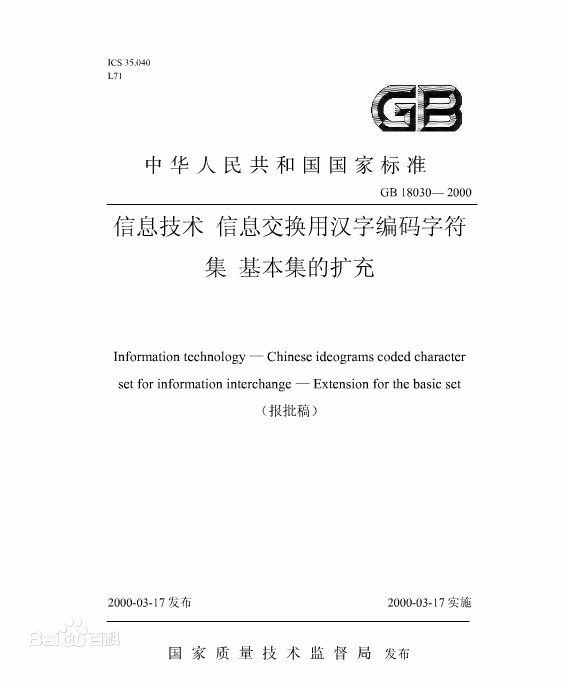
常见字体格式及编码资料
常见的字体格式有 TTF、EOT,一般使用 TTF。
TTF(TrueTypeFont)是Apple公司和Microsoft公司共同推出的字体文件格式,随着windows的流行,已经变成最常用的一种字体文件表示方式。
字库是输出设备的一个组成部分。由于汉字不同干西方字体,字符集非常庞大,不能用单字节表示,因此postscript level i的rip不能使用汉字,很多西文软件也不支持汉字。
桌面出版系统使用的字库有两种标准: postscript字库和truetype字库。这两种字体标准都是采用曲线方式描述字体轮廓,因此都可以输出很高质量的字形。
常用的字库标准是truetype字库,truetype字体是windows操作系统使用的唯一字体标准,macintosh计算机也用 truetype字体作为系统字体。
truetype字体的最大优点是可以很方便地把字体轮廓转换成曲线,可以对曲线进行填充,制成各种颜色和效果,它可以进一步变形,制作特殊效果字体,因此经常用来制作一些标题字或花样字。
truetype字便宜,字款丰富。
但一般情况厂truetype字不能直接由rip输出。需要经过特殊处理,比如转成曲线或输出时下载,使用起来较麻烦。速度也要慢一些,尤其是处理大量文字时很不方便,因此不适合用来作为页面的正文文字使用。
truetype字体也用来作为postscript字库的显示字用,各字库公司同时都有这两种标准的产品。
因此当使用truetype字体制作版面时,输出时仍然可以将它代换成postscript字库输出
在一些特殊的场合,系统字符集不包含你要用的字体,这时候必须使用自己的字体文件,如甲骨文等古文字处理,一般在系统盘\WINDOWS\Fonts里,直接双击能查看是什么样的字体。
字体编码
字体编码,一般称之为字形码,是用于将字符编码(内码,如GBK、UTF-16、BIG5等)所表示的文字以图像的形式在屏幕或打印机上表现出来的编码。
在Windows系统下,常见的字体编码有TTF和OTF格式,用于表示宋体、黑体等各类字体。
附带说一句,简体中文版的Windows XP自带的MingLiU和PMingLiU等字体选择CHINESE_BIG5字符集即可显示BIG5编码的文字,无需额外下载专门的BIG5码字体。注意:Windows自带的记事本程序识别文字时,是将它所能识别的字符编码全部转化为UTF-16的编码形式,再调用字体编码来显示,因此简体中文版系统的记事本程序中选择MingLiU字体仍不能正确显示BIG5码文字。如需查看BIG5码文字,请使用MS Office、Ultra Edit等文本编辑器。
字符集
① GB2312-80字符集,中文名国家标准字符集(GB=GuóBiāo国标)。收入汉字6763个,符号715个,总计7478个字符,这是大陆普遍使用的简体字字符集。楷体-GB2312、仿宋-GB2312、华文行楷等市面上绝大多数字体支持显示这个字符集,亦是大多数输入法所采用的字符集。市面上绝大多数所谓的繁体字体,其实采用的是GB-2313字符集简体字的编码,用字体显示为繁体字,而不是直接用GBK字符集中繁体字的编码,错误百出。
② Big-5字符集,中文名大五码,是台湾繁体字的字符集,收入13060个繁体汉字,808个符号,总计13868个字符,普遍使用于台湾、香港等地区。台湾教育部标准宋体楷体等港台大多数字体支持这个字符集的显示。
③ GBK字符集,中文名国家标准扩展字符集(GB=GuóBiāo国标;K=Kuò扩,即扩展),兼容GB2312-80标准,包含Big-5的繁体字,但是不兼容Big-5字符集编码,收入21003个汉字,882个符号,共计21885个字符,包括了中日韩(CJK)统一汉字20902个、扩展A集(CJK Ext-A) 中的汉字52个。Windows 95/98简体中文版就带有这个GBK.txt文件。宋体、隶书、黑体、幼圆、华文中宋、华文细黑、华文楷体、标楷体(DFKai-SB)、Arial Unicode MS、MingLiU、PMingLiU等字体支持显示这个字符集。微软拼音输入法2003、全拼、紫光拼音等输入法,能够录入如镕镕炁夬喆嚞姤赟赟䶮龑昳堃慜靕臹等GBK简繁体汉字。
Big-5 (台湾繁体字)与GB2312-80 (大陆简体字),编码不相兼容,字符在不同的操作系统中便产生乱码。文本文字的简体与繁体(文字及编码)之间的转换,可用BabelPad、TextPro或Convertz之类的转码软件来解决。若是程序,Windows XP操作系统,可用Microsoft AppLocale Utility 1.0解决;Windows 2000的操作系统,大概只有用:中文之星、四通利方、南极星、金山快译之类的转码软件方能解决了。
④ GB18030-2000字符集,包含GBK字符集和CJK Ext-A 全部6582个汉字,共计27533个汉字。宋体-18030、方正楷体(FZKai-Z03)、书同文楷体(MS Song)宋体(ht_cjk+)、香港华康标准宋体(DFSongStd)、华康香港标准楷体、CERG Chinese Font、韩国New Gulim,以及微软Windows Vista操作系统提供的宋黑楷仿宋等字体亦支持这个字符集的显示。Windows 98支持这个字符集,以下的字符集则不支持。手写输入法逍遥笔4.0版支持GB18030字符集及方正超大字符集汉字的录入。
⑤ 方正超大字符集,包含GB18030-2000字符集、CJK Ext-B中的36862个汉字,共计64395个汉字。宋体-方正超大字符集支持这个字符集的显示。Microsoft Office XP或2003简体中文版就自带有这个字体。Windows 2000的操作系统需安装超大字符集支持包“Surrogate更新”。
⑥ GB18030-2005字符集,在GB13030-2000的基础上,增加了CJK Ext-B的36862个汉字,以及其它的一些汉字,共计70244个汉字。
⑦ ISO/IEC 10646 / Unicode字符集,这是全球可以共享的编码字符集,两者相互兼融,涵盖了世界上主要语文的字符,其中包括简繁体汉字,计有:CJK统一汉字编码20992个、CJK Ext-A 编码 6582个、CJK Ext-B 编码 36862个、CJK Ext-C 编码 4160个、 CJK Ext-D 编码 222个,共计74686个汉字。SimSun-ExtB(宋体)、MingLiU-ExtB(细明体)能显示全部Ext-B汉字。目前有 UniFonts 6.0 可以显示Unicode中的全部CJK编码的字符,输入法可用海峰五笔、新概念五笔、仓颉输入法世纪版、新版的微软新注音、仓颉输入法 6.0 版(单码功能)等输入法录入。Ext-C还有2万多个汉字。详情请参阅香港中文大学网站、马来西亚仓颉之友网站、福建陈清钰个人网站。
⑧ 汉字构形数据库2.3版,内含楷书字形60082个、小篆11100个、楚系简帛文字2627个、金文3459个、甲骨文177个、异体字12768组。可以安装该程序,亦可以解压后使用其中的字体文件,对于整理某些古代文献十分有用。
如果超出了输入法所支持的字符集,就不能录入计算机。有些人利用私人造字区PUA的编码,造了一些字体。一些如果没有相应字体的支持,则显示为黑框、方框或空白。如果操作系统或应用软件不支持该字符集,则显示为问号(一个或两个)。在网页上亦存在同样的情况。
(2)已做好的Illustrator文件在电脑中打开时,软件报字体缺失错误,之后,以另外的字体代替,从而引致设计被更改。
就有许多是一般电脑中没有安装的字体,而且某些字体无法被Illustrator识别。如果在其他电脑中打开,会报字体缺失。
如何解决这一问题呢?
很多人现在的做法是:在Photoshop中打好文字设置好字体再复制后粘贴到Illustrator中,这样非常麻烦而且效率很低。
解决方法:
(1)修改注册表法(对电脑不太熟悉者慎用!):
先将Windows下的整个Fonts目录复制到根目录下,然后打开注册表(注意在打开之前备份),找到HKEY_LOCAL_MACH INE/Software/Microsoft/Windows/CurrentVersion键,删除整个Fonts子键,之后再重建一新的Fonts子键,退出注册表,重启系统,打开控制面板,选择“字体→安装新字体→根目录下刚才复制过来的Fonts目录→所有字体安装”,OK,再重启系统。
(2)把字体放在临时目录下:
将字体放在Illustrator软件安装目录中的字体相关目录(临时目录)下,比如:C:/Program Files/Adobe/Illustrator CS/Fonts/Composite Fonts/Temp
比如:你需要使用方正剪纸简体和汉仪菱心体简体,那么,你可以将“方正剪纸简体.ttf”和“汉仪菱心体简.ttf”这两个字体文件COPY到上述目录中。
之后,你会发现,Illustrator字体列表中就可以选择这些字体了。不过,需要注意的是,由于是“临时目录”,所以,在Illustrator软件退出时,它将尝试清理这些临时目录,如果不做处理,下次你打开上述AI文件时,又会报字体缺失!要避免这种情况,可以:(1)将缺失的字体转成曲线;这样做的缺点时,下次如果需要再修改文字,就必须重新打字,所以不推荐这么做;(2)避免Illustrator清理:做法是,将上述字体文件改为只读。全选临时字体目录下的所有你想保留的字体文件,按右键,属性,将只读前的选框勾中,确定即可。下次,你就没有这个烦恼了。